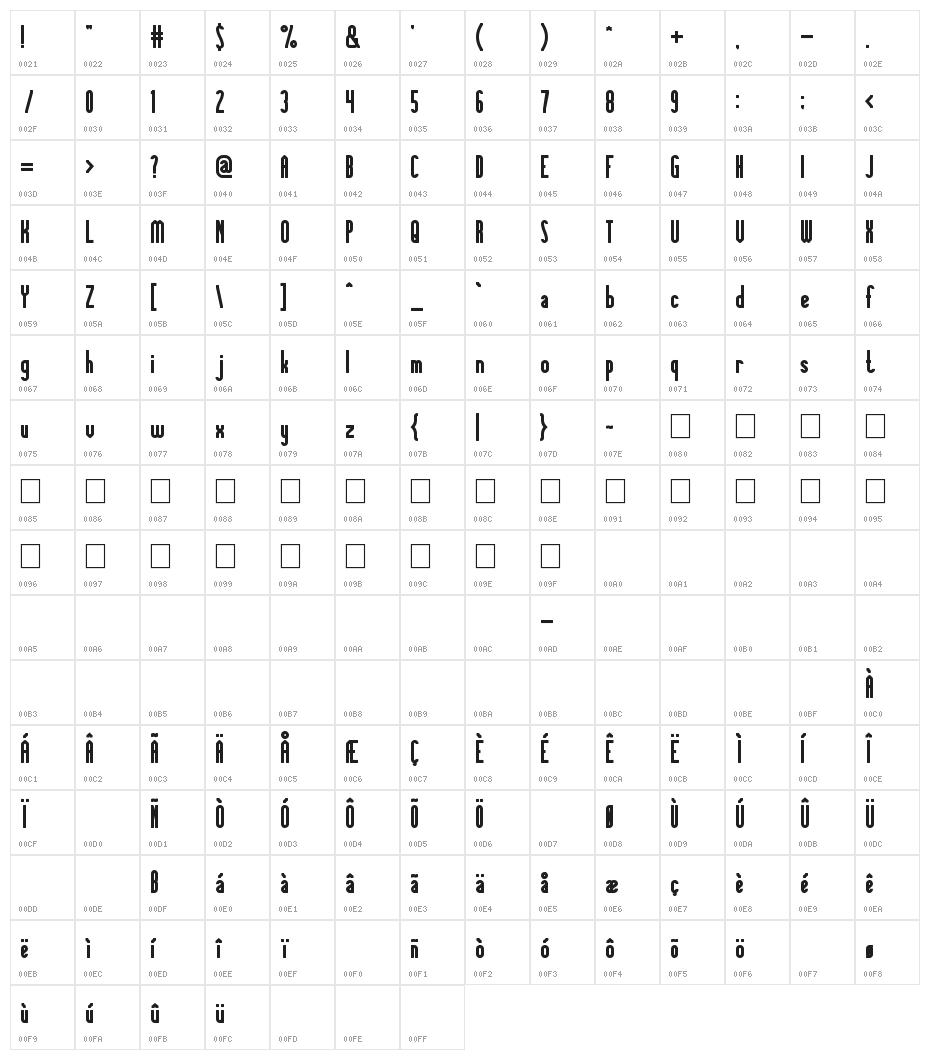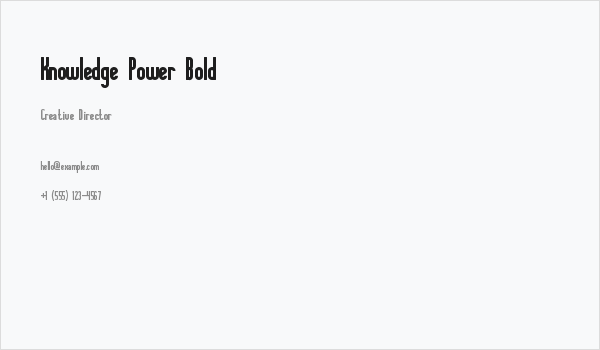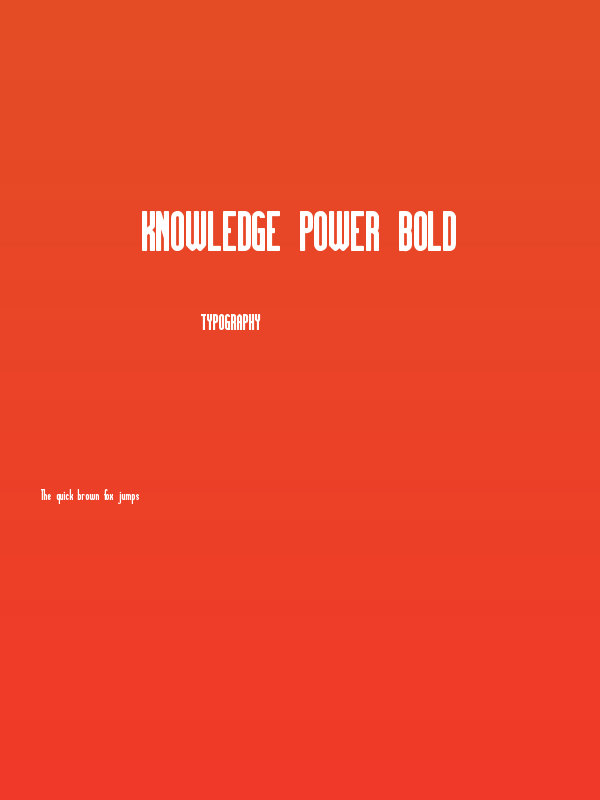
Knowledge Power Bold Font
| Nome | Knowledge Power Bold |
| Peso | Bold |
| Progetti proposti | Ideal for headlines, posters, branding, and any project requiring a bold statement. |